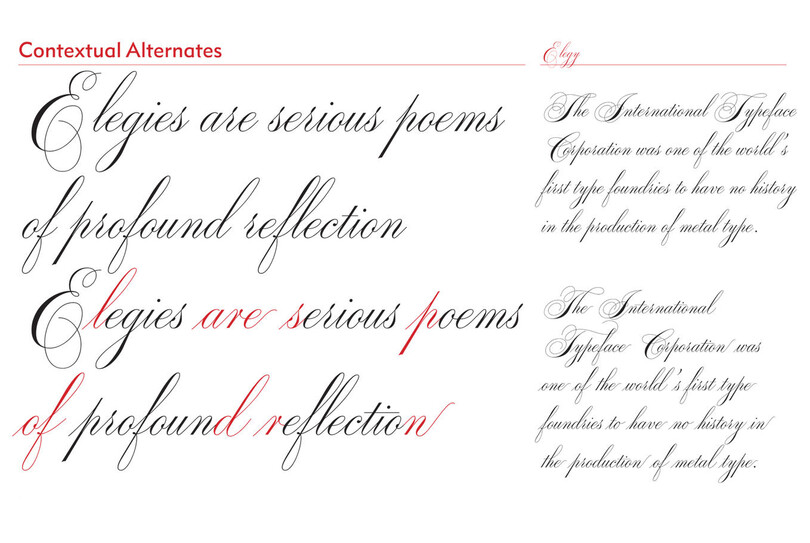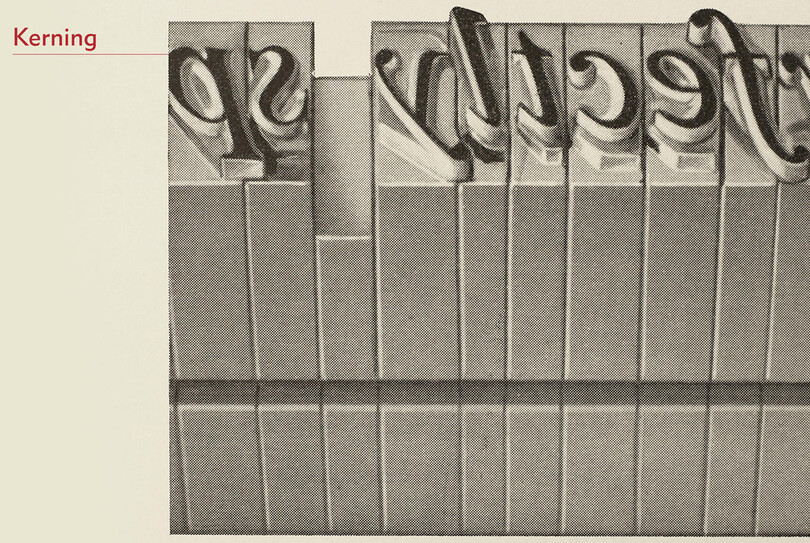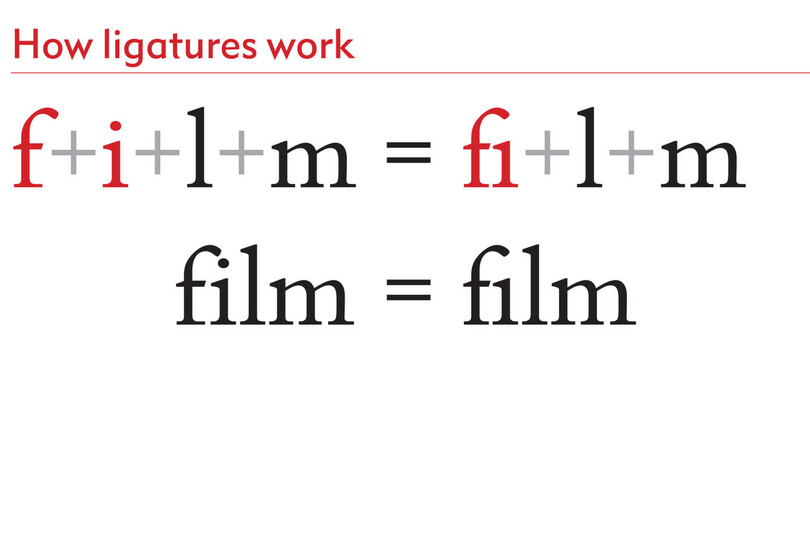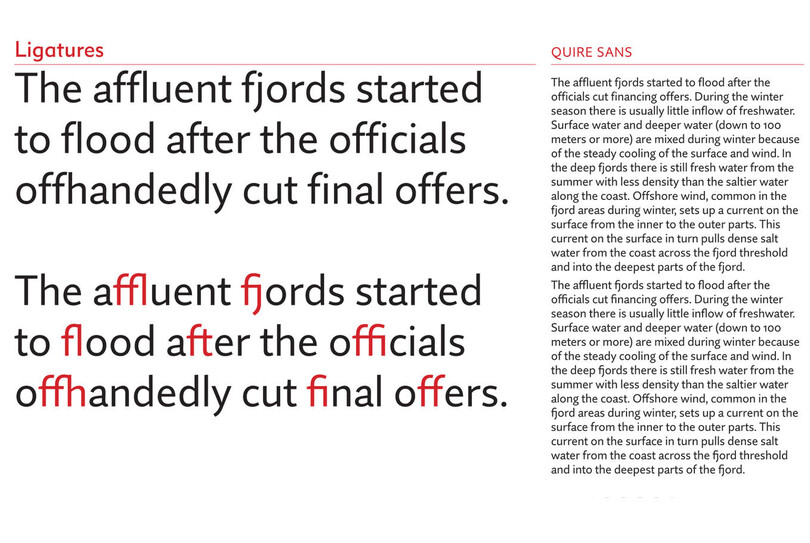
Q&A:Dan Rhatiganがウェブフォントについて語る
「 Just seeing pro doesn't mean it’s going to have OpenType features. 」
ウェビナー「プロが教えるウェブフォントの選び方」では、書体デザイナーのDan Rhatiganがインターフェイスでのフォントに関する厳しい条件について説明。フォントのサイズから間隔、色、スタイルに至るまで、スマートなウェブフォントの作成に関する実用的なアドバイスを教えてくれました。プレゼンテーションの後、参加者からの質問に答え、ウェブフォントの選び方、購入前にフォントを試すことのできる便利なツール、エンベッドアプローチについて解説しています。下記の概要をご参照ください。
本文コピーでの書体の色について、何かお勧めはありますか。
長い文章の場合は、読者にじっくり読んでもらい、気が散らないようにしたいですから、白の背景に黒字が一番良いでしょう。レンダリング環境では、黒字のテキストが画面でできるだけくっきりと見えることを目的に調整されています。白の背景にダークグレーの文字で読みやすい例も多くありますが、それは黒と白の組み合わせと同じことです。つまり原則として、背景と文字のコントラストが高いほど読みやすいのです。ですから、黒い文字をダークグレーにしても構いません。ダークグレーでも可読性はかなり高いです。しかし、文章が長くなると、それが若干難しくなります。だいたい1段落程度なら、多少コントラストが低くても可読性に影響はありません。
ウェブフォントでは、イタリックはデザインし直し、文字間にさらに余白を加え、画面を埋め尽くさないようにしてあるのではないですか。
フォントがウェブ用にデザインし直されている場合だけです。ウェブフォント用と呼ばれているからといって、必ずしもウェブで見栄えがするようにデザインされているわけではありません。デスクトップ版のフォントを、ウェブ表示用に調整したという意味なのです。ですから「ウェブフォント」という呼称が保証しているのは、フォントデータがウェブブラウザで表示可能ということだけで、ヒンティングの (鮮明に見えるようソフトウェアのレイヤーが追加されている) 場合もあります。
例えば、ITC Galliard® Italicはウェブフォントです。しかし、ITC Galliard® ItalicをITC Galliard® eText Italic [上図] と比較すると、eText Italicが再デザインされ、オープンでクリアになっているのがわかるでしょう。ファミリーを見てどのスタイルがウェブで使えるのかを考えるだけではなく、例えばそのイタリックがウェブでやりたいことに適切なデザインなのかどうかを自分の目でしっかりと見て、判断しなければなりません。PMN Caecilia® eTextもウェブ用に再デザインされたもので、画面上のテキストにぴったりの書体です。slab serif体ですから低コントラストで、イタリックでも細くなりません。serif体もあり、鮮明さを維持できます。
フォントがウェブ用に再デザインされたかどうかを見分ける方法はありますか。
開発者が時間をかけて画面で読みやすいよう書体をデザインしたり、再デザインしていれば、自慢して宣伝するからわかります。再デザインは書体デザインのクオリティとしても重要で、セールスポイントですから、消費者に是非知って欲しい点なのです。Monotypeフォントの場合、名前にeTextが付いていれば、これは大きく安定性を持たせ、ウェブのテキストサイズで鮮明な表示ができるよう一から再デザインされているという意味です。Hoefler & Co.はScreenSmartコレクションを、Font BureauはReading Edgeシリーズを扱っています。
今までデスクトップフォントでは存在していなかった、まったく新しい書体はどうですか。画面上での使用のために最適化された、高品質のウェブフォントと思って良いのでしょうか。
必ずしもそうとは言えません。デザイナーは様々な目的で書体をデザインするからです。ですから、大切なことを説明します。
• ここに挙げる例のように多くのフォントを見て、目のトレーニングをしてください。フォントが読みやすいかどうかを判断する最適な方法です。自分の目を信頼し、多くの例を見ることです。
• ブラウザでウェブフォントを試し、うまく表示され、環境や作業に適していることを確認してください。テストを重ねることで、それが最適な選択であるかどうかをしっかりと判断することができます。
フォントを購入する前に画面上でウェブフォントをいろいろなサイズでプレビューできるツールで、お勧めのものを紹介していただけますか。
MonotypeのTypecast™を試してみてください。ブラウザベースのウェブデザインツールで、Monotype、Fonts.com、MyFonts ウェブフォントライブラリすべてとその他のプロバイダのフォントライブラリを収録しています。サインアップは無料で、書体のプレビュー、設定、スケーリングでき、ウェブページのプロトタイプの作成もできます。Photoshop カンプで作業するのではなく、ブラウザで書体を見て、実際にどのように表示されるかを確認できるのは、素晴らしいことです。
@font faceを使ってフォントを埋め込むのと、Javascriptでライブラリに持ってくるのとどちらが良いでしょうか。
基本的には、@font-faceよりキットの方が良いでしょう。Typekitに、この件に関するとても良いブログ記事が掲載されています。Javascript/キットには、多くの利点があります。
• Javascriptにより、ページ上で何が起きているか判断できます。「フォントの読み込みができているか。まだ?じゃあ、クラスを追加して、フォールバックスタイルを適用してFOUTに対処しよう。」
• キットを使用すれば、クロスブラウザーの心配がなくなります。ウェブブラウザは、一定のフォントファイルタイプのみに対応しています。複数のフォールバックファイルから自分で選定する代わりに、キットが自分の@font-faceルールに準じたファイルを特定して読み込んでくれます。
• プロバイダキットからのフォントは、自分でホスティング(@font-faceを使用したときによくある) するのではなく、一般には超高速のCDNでホスティングされます。プロバイダによっては、使用するCSSに生フォントデータを埋め込み、HTTPリクエストを削減してパフォーマンスを向上させます。
@font-faceと比較した際、Javascriptを使用する場合の明確なデメリットは、ユーザーがブラウザでJavascriptを無効にしている場合にフォントが読み込まれないという点です。ただし、この可能性はかなり低いのです。その理由は、1) Javascriptは、現在のインターネットに不可欠の技術であること。2) Javascriptを無効にすると、ウェブブラウジングそのものの機能が大幅に損なわれ、フォントが読み込まれないどころの問題ではなくなるからです。
長いアンケートなどの長文のコンテンツにお勧めのウェブフォントは何ですか。Helvetica®ですか。
いろいろなオプションが考えられますが、長文の場合はすごく小さなテキストサイズでの読みやすさを最大限に考え、大文字のI、小文字のl、数字の1など、読み手が混乱しがちな文字を簡単に判別できるようにしたいものです。
Helvetica®はかなり良い選択肢ですが、それを若干調整したNeue Helvetica® eTextの方がはるかにクリアです。ですから、読みやすさが長所になっています。けれども、前述した文字の可読性は少し厄介です。これはsans serif体の多くに共通する問題です。
個性を出したい場合は、2階建てのAや2階建てのGなどのディテールのあるはっきりとしたsans serif体を使用すると、文字の判別がしやすく、テキストがとても読みやすくなります。
プレゼンテーションで2種類のウェブフォントのオーバーレイを見せていただきましたが [上図参照]、同じサイズなのですか。
まったく同じフォントサイズです。2行目は、行の高さがゼロになっていますから、重なっています。しかし、書体の描画で、テキストのサイズがいかに違って見えるかをうまく表しています。ある書体の16pxは、別の書体の16pxより大きく見えたり、小さく見えることがあります。デザインのプロポーションそのものが、実際に見えるサイズに大きく影響します。
インターネットで常にきれいに表示できる主力のウェブフォントは何ですか。
優れたフォントは一番人気が出ますから、MyFontsやFonts.com、その他のポータルのベストセラーになっているフォントから始めるのが良いと思います。低コントラストで大きく、ゆったりとプロポーションをとったsans serif体をよく見かけます。Helvetica®やFrutiger®、Museo Sans™、Brandon Grotesqueなどです。通常、くっきりとしてオープンなタイプが画面上のテキストに最適です。
デザイナーとプログラマーとの間の考え方の差を埋めるのが難しいことがよくあります。ウェブデザイナーがプログラマーに行間や文字間隔を指定するにあたって、ベストな方法は何ですか。
Typecast™に戻りますが、馴染みのあるフロントエンドの視覚コントロールを使用し、ブラウザでページのプロトタイプ作成ができます。デザイナーは目で見ながら作業をしますが、バックグラウンドではCSSとHTMLの作業が行われています。レイアウトを希望通りに仕上げたら、HTMLとCSSを出力し、デベロッパーに渡します。これが、自分が制作したデザインの詳細記録になります。デベロッパーは、そのPhotoshop カンプを解釈する手間が省けるわけです。「そのテキストはこのサイズかな、あのサイズかな」「それは同じ書体なのかな、それともちょっと違うのかな」「行の長さは480px or 500px相当かな」などと考える必要がなくなるのです。
私は、代理店や出版社で数多くのプレゼンテーションに出席し、デザイナーとデベロッパーの両方がいるチームに、まさにこの質問について説明し、Typecastの仕組みを紹介してきました。毎日、現場でこのような問題に取り組んでいるチームは、このツールによって可能になる内容を知り、本当に喜んでいました。デザイナーにもう少しビジュアル的な思考で作業してもらいながらも、デベロッパーが理解できるCSS構文でこれらの決定事項を説明し、デザインを納品が出来ることに、多くの感嘆の声があがりました。納品後の訂正の手間が省け、デザインと開発プロセスが密接になるのです。
PMN Caecilia®などのストロークのコントラストが少なく、はっきりとした角度のserif体は、sans serif体と同じように画面映えがします。
ウェブサイトでは、serif体とsans serif体のどちらが良いですか。
Serif体のフォントは、書体デザインとしてディテールが細かいので、ウェブやインターフェイスではやりにくいと思います。これはテキストサイズが1em/12px–16px の場合です。Serif体を使うのであれば、Century®、PMN Caecilia®、Clarendon®、Georgia®のような低コントラストでディテールがくっきりしていて、直線でしっかりした角度のserif体を検討してください。今挙げたものは、ディテールが細かすぎず、比較的扱いやすいものです。特に本文テキストには、Didot®などの線が細すぎる書体は避けましょう。